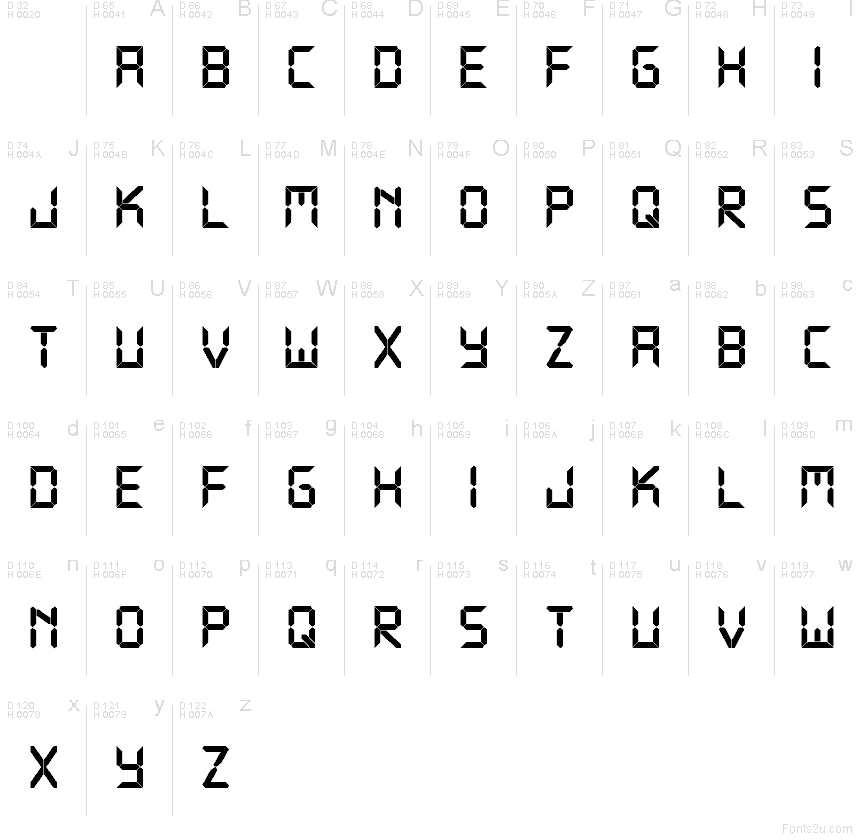
Fake Hope Extravagant od Vladimíra Nikoliće je bezplatné digitální titulkové písmo se širokou, segmentovanou konstrukcí nadrozměrných LED nápisů a výrazným sci-fi nádechem. Jeho verzálky jsou široké, hranaté a v místech spojů záměrně přerušené.
Na plakátech elektronické hudby, klubových letácích i arkádových grafikách působí přísná geometrie spíše jako podsvícené rozhraní než neutrální písmo. Stejný segmentovaný vzor se uplatní také na obalech technologií a sportovním merchandisingu, kde useknuté tahy evokují schémata zapojení, časomíry a světelné panely průmyslových zařízení.
Písmo „Fake Hope“ je k dispozici ve verzích Regular a Filled.